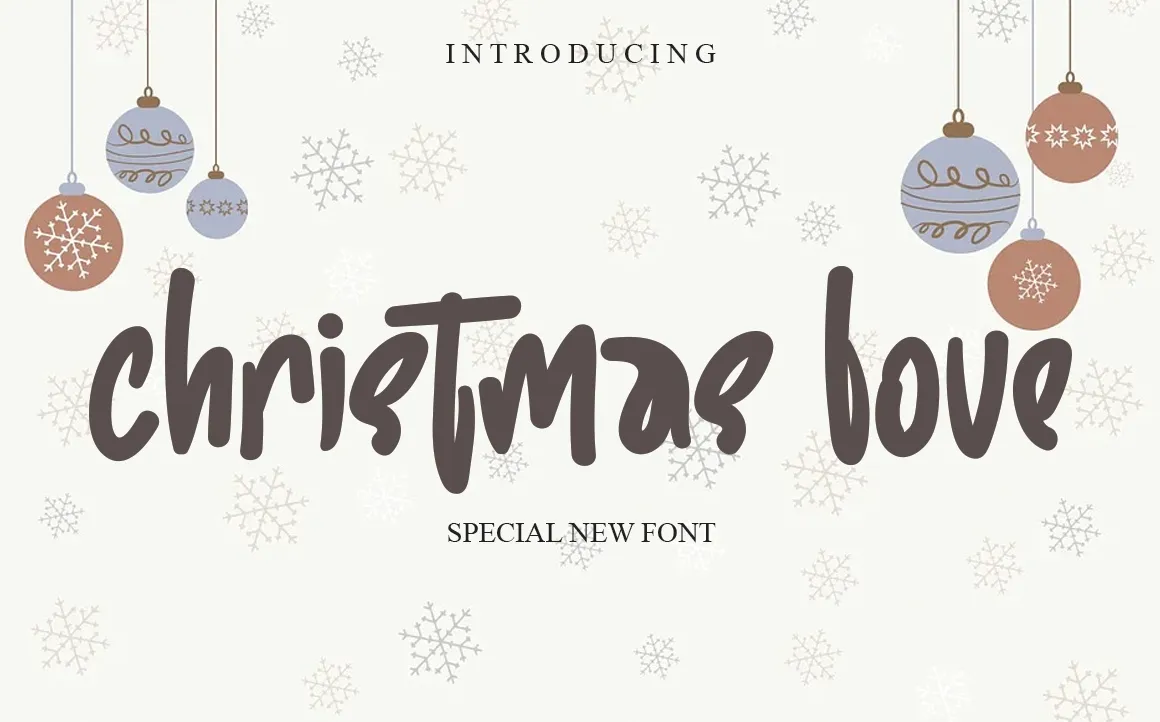
Christma Love Font – Download Grátis
Esta é uma fonte escrita a mão única e divertida, perfeita tanto para uso em redes sociais como para escrever com estilo em projetos DIY. Ideal para quem busca personalidade em suas criações digitais, este é um recurso de escrita a mão que irá transformar qualquer ideia criativa em uma obra de arte. Com o levincreative Christma Love Font, você pode decorar seu próximo projeto social ou adicionar um toque especial ao seu próprio design, sempre garantindo a personalidade e a elegância que a escrita a mão promete. Não perca esta oportunidade para deixar sua marca única em cada fonte usada!